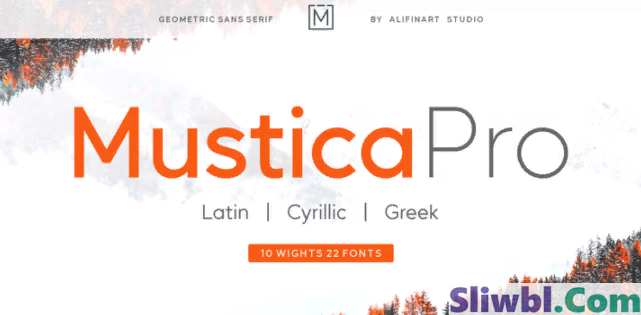
Mustica Pro - это чистый и геометрический шрифт sans serif, обладающий рядом особенностей OpenType и поддерживающий латинский, кириллический и греческий языки.
Слово Mustica имеет значение короны, даже для азиатов это слово не только "корона". Но также Mustica имеет значение храброго, умного или мудрого.
В связи с этим шрифт Mustica Pro был тщательно разработан с оптимальными усилиями, чтобы сделать его самым популярным современным sans serif.
Mustica Pro имеет множество преимуществ, помимо достаточно широкой языковой поддержки. Среди важных особенностей - чувствительность к регистру, лигатуры, произвольные лигатуры, пропорциональные цифры, табличные цифры, цифры старого стиля, пропорциональный старый стиль, дроби, числитель, знаменатель, надстрочный знак (научный высший), низший, дробь, выравнивающее двоеточие и другие.
С теми возможностями, которыми обладает шрифт Mustica Pro, можно надеяться, что этот шрифт станет лучшим профессиональным выбором.
Более того, полный пакет семейства включает в себя весовую вариацию от волосяного начертания до черного.
По этой причине Mustica Pro идеально подходит для использования в качестве основного шрифта в различных дизайнерских и коммерческих проектах.